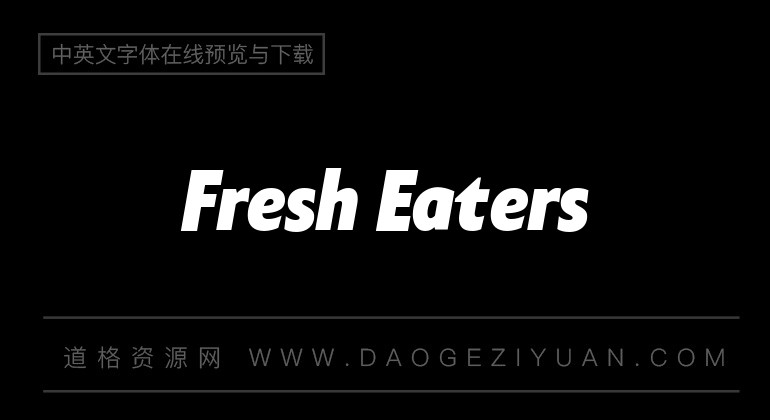
Fresh Eaters
Fresh Eaters 是一款现代、明亮的字体,具有细节丰富的外观,灵活的结构和有趣的设计。它的字体结构具有独特的特点,具有圆润的曲线,宽松的字形,以及大胆的笔画,可以提供一种有趣的、活泼的结构。它可以用于任何类型的文本,尤其是在平面设计中,可以使文本看起来更有活力,更有吸引力。
Fresh Eaters是一款非常不错的手写艺术字体,具有很好的视觉感,适合于文化类的宣传设计、商业类品牌的广告和产品包装设计以及个性化文字排版等较多场景。